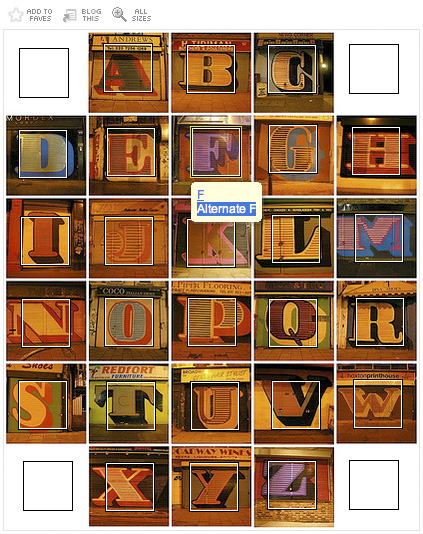
Lichtscheues Großstadt AlphabetDrei Nächte war der Londoner-Fotograf Dave Gorman auf der
Pirsch, um ein komplettes Graffiti-Alphabet des Zeichners Eine vor die
Linse zu bekommen, das erst bei geschlossenen Geschäftsrollläden
erscheint. Am Tag 1 fragte sich der Typo-Jäger noch: »Hat er alle
26 Buchstaben gezeichnet?« 48 Stunden später stand die Antwort
fest: Ja! Nun hat Gorman die Fotos auf flickr ausgestellt,
aufbereitet mit einer Eleganz, wie sie keine andere Foto-Datenbank zulässt.
Jonathan Hoefler erwähnte auf Typographica erstmals die Fotoserie und betonte
das gestörte Verhältnis von Graffiti und Typografie: »Graffiti
and typography have an odd relationship. Judging from the number of graffiti fonts out there, it seems that every
type designer passes through a romance with the stuff. It’s certainly true
that watching handwritten forms rasterize before you on screen can be truly
beguiling, and there’s a perverse and private pleasure to using exacting
Bezier curves to render the esprit of the marker.«